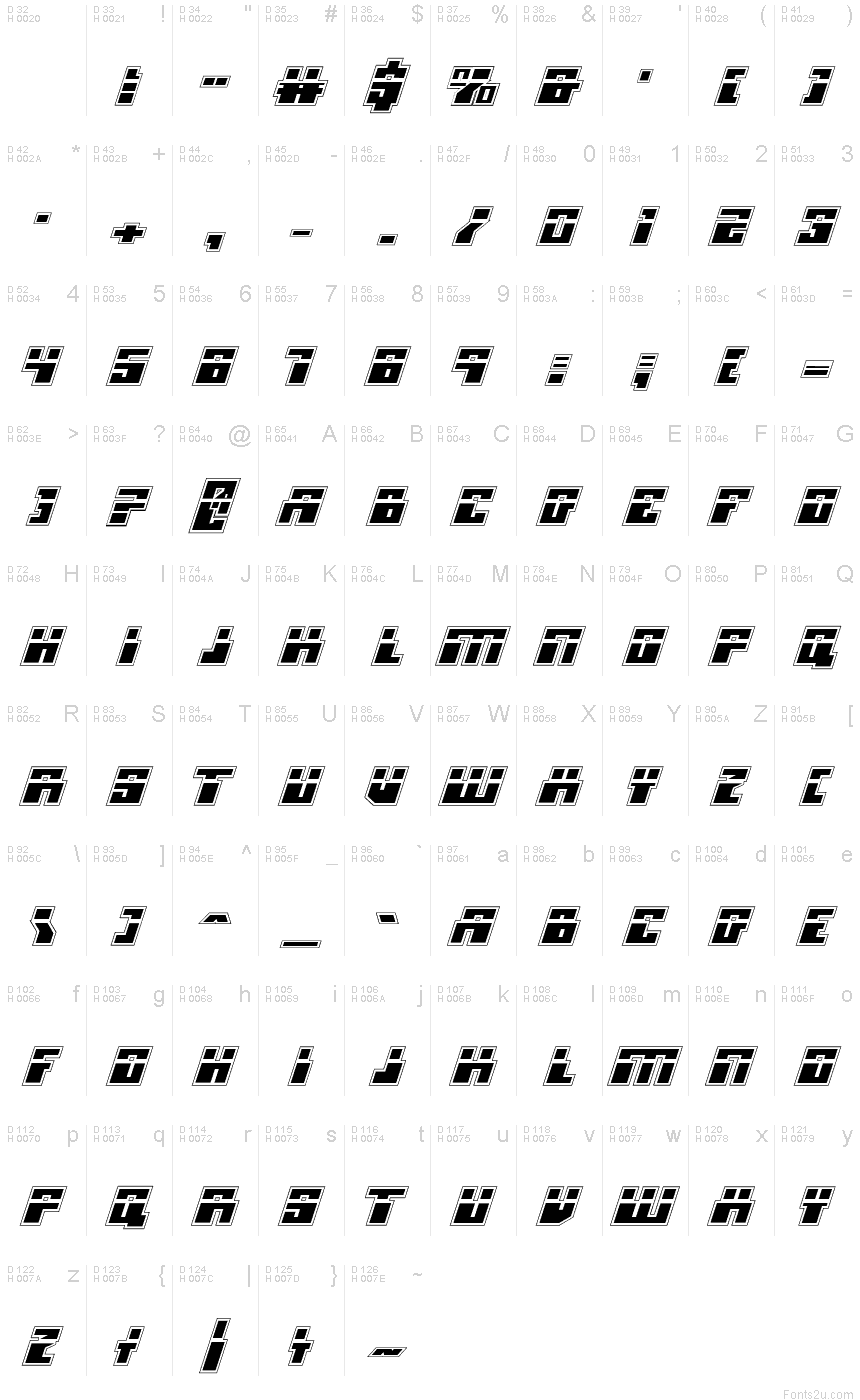
Micronian Laser Academy Italic von Iconian Fonts ist eine kostenlose futuristische Display-Schrift, die aus breiten schrägen Großbuchstaben und scharfkantigen geometrischen Schnitten aufgebaut ist. Ihre doppelt linierte Kontur und die eingefügten Zwischenräume verleihen dem Schriftbild eine mehrschichtige, maschinell erzeugte Oberfläche.
Gaming-Titelkarten sind ihr offensichtlichster Einsatzbereich, wobei die Vorwärtsneigung und die eckige Konstruktion auch zu Science-Fiction-Plakaten, Arcade-Branding und Merchandise für elektronische Musik passen. Im Editorial Design können die konturierten Formen eine Technik-Artikelüberschrift in eine benutzerschnittstellenähnliche Grafik verwandeln.
Micronian Laser Academy Italic